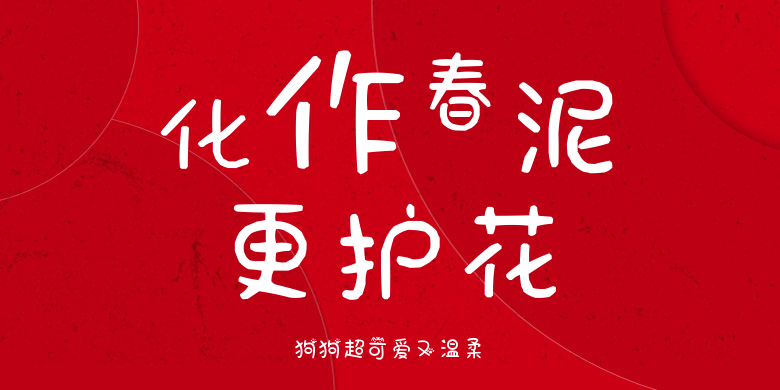
狗狗超可爱又温柔
狗狗超可爱又温柔,这款字体结构工整、笔画清晰,兼顾美观与易读性,适用于标题、正文、海报、包装、LOGO 等多种场景。字形优雅稳定,风格百搭耐看,适配日常排版与创意设计,让文字呈现更舒适、更具质感。狗狗超可爱又温柔一笔一画,皆是细节,以均衡的比例、流畅的线条打造舒适视觉体验,字形端正大气,风格简约现代。无论是商业设计、品牌宣传还是日常排版,都能轻松驾驭,让文字更有格调与力量。狗狗超可爱又温柔字体下载。